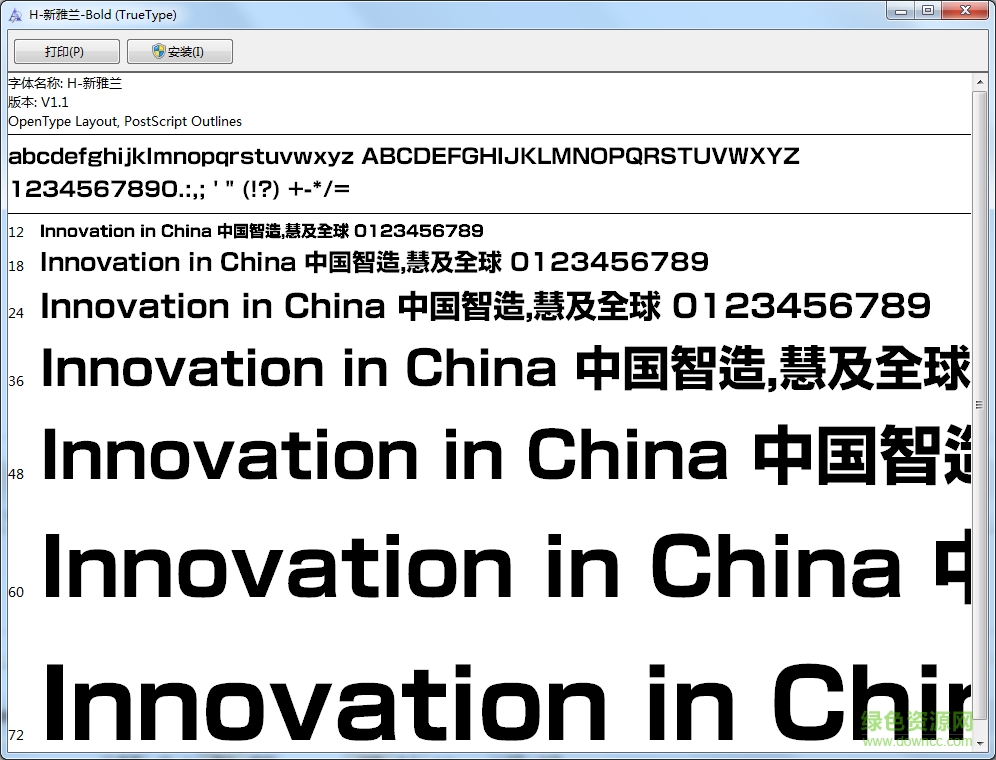
新雅蘭字體ttf
新雅蘭字體是一款非常好看的字體,字體工整,略微偏矮胖型,自帶加粗特效,十分的醒目,可用于廣告制作和藝術(shù)設(shè)計,歡迎大家到綠色資源網(wǎng)下載使用!
官方介紹
一筆一畫規(guī)規(guī)矩矩。該新雅蘭字體適用于包裝印刷、廣告設(shè)計、報紙周刊等領(lǐng)域